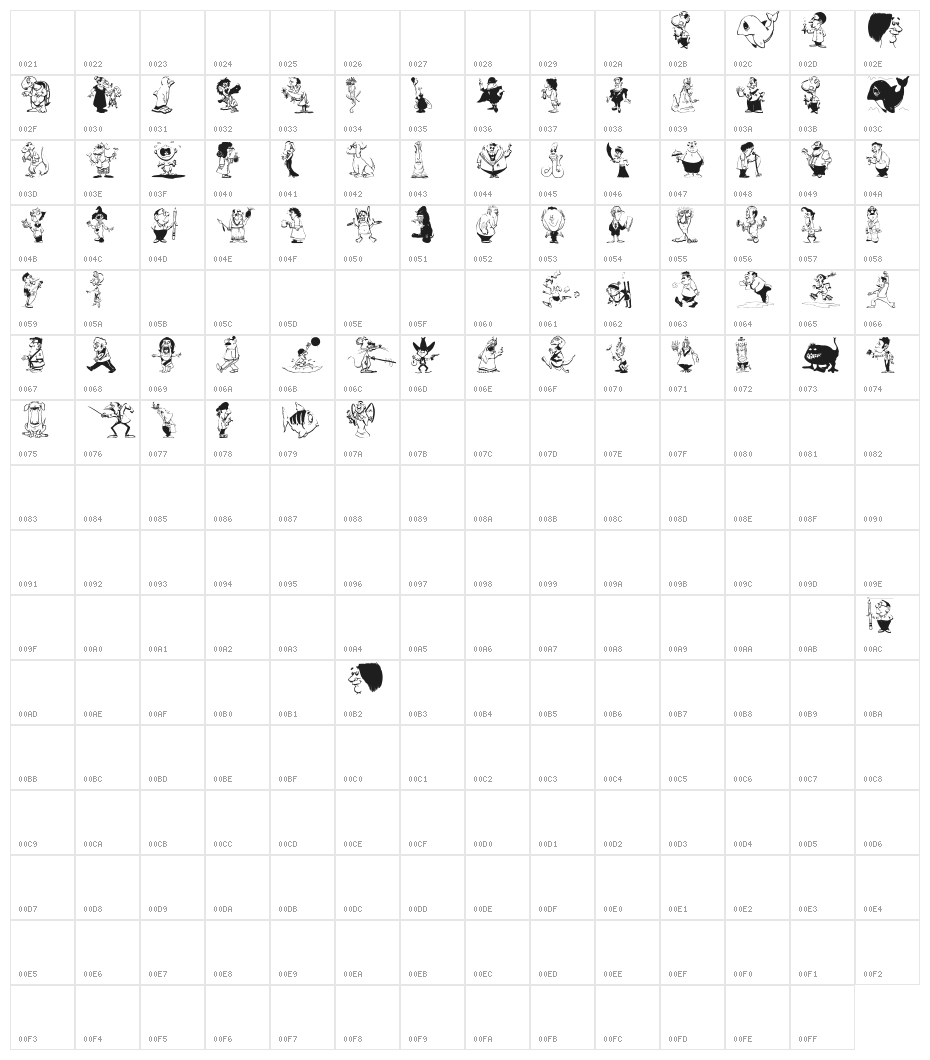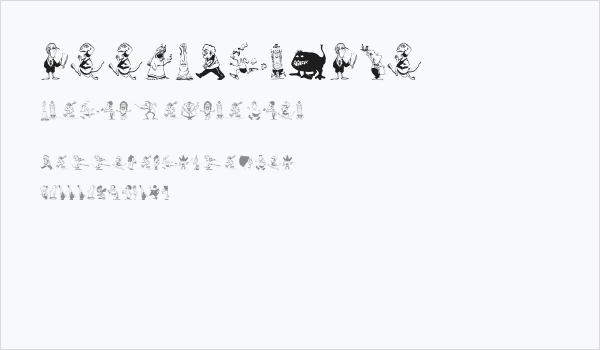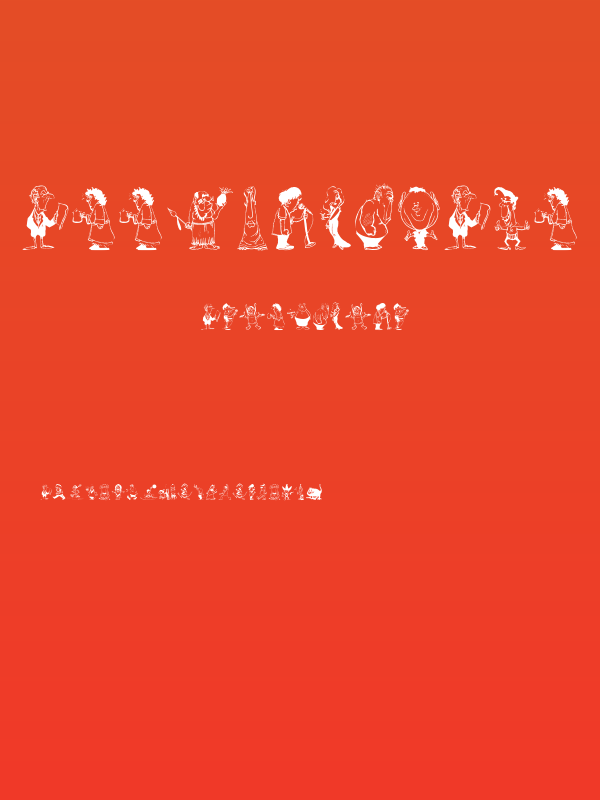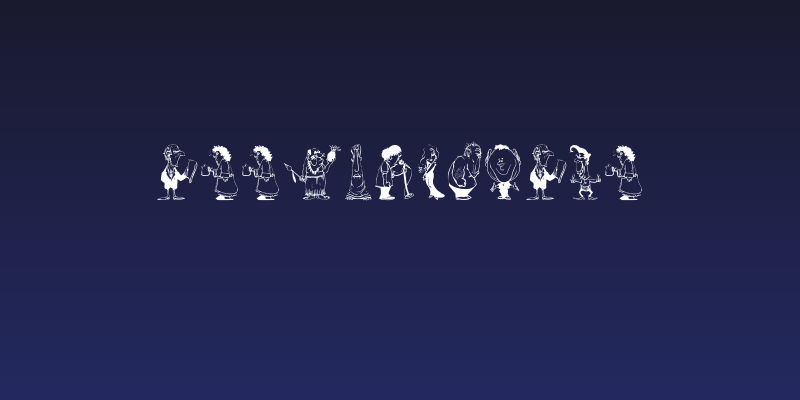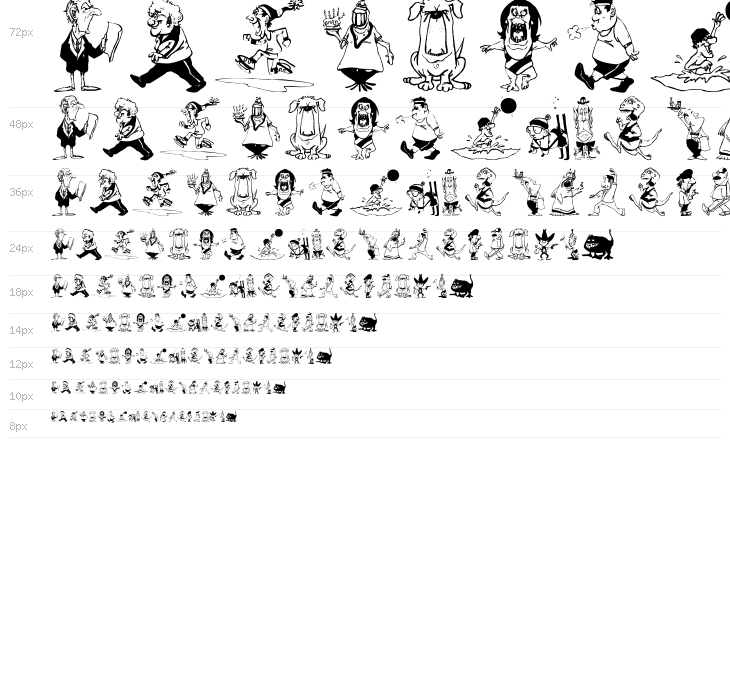
ToonCharsTwo Font
| 全体的なスタイル | Whimsical, Playful, Cartoonish, Decorative |
| 用途 | Headlines, Posters, Logos, Themed event materials |
| おすすめプロジェクト | Children’s books, comic titles, party invitations, playful branding, educational materials, greeting cards. |